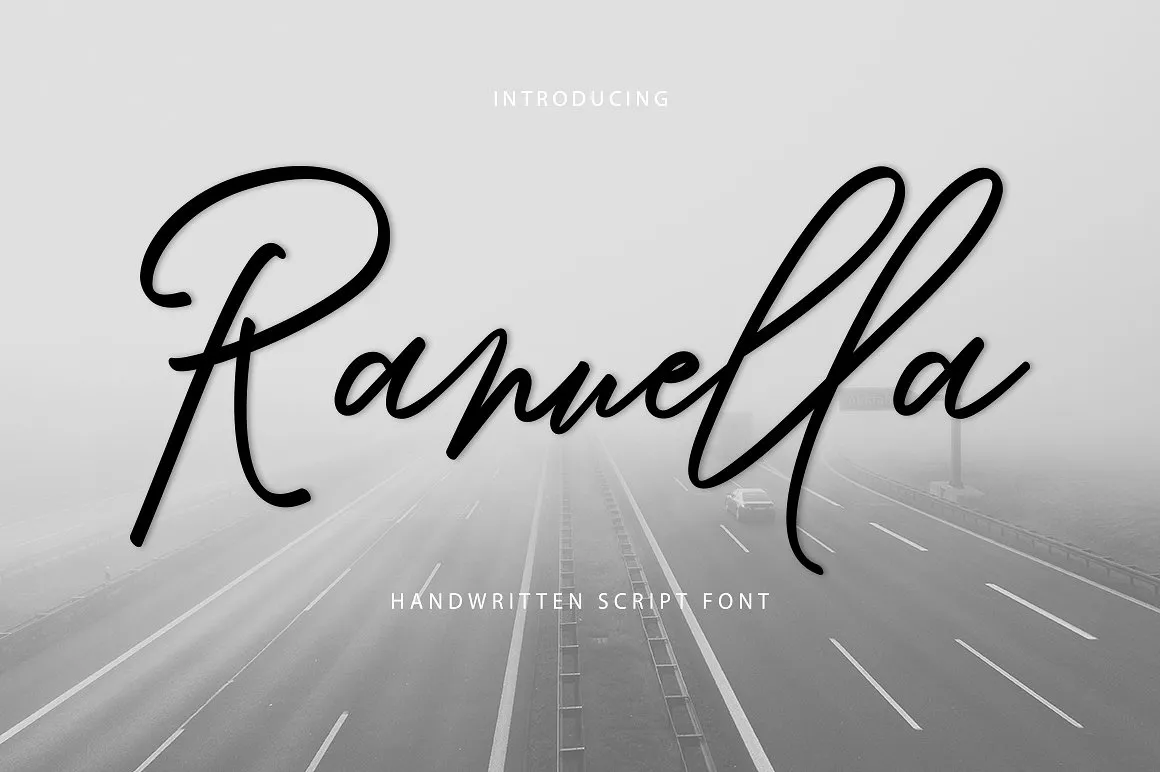
Ranuella Script Font – Download Grátis
Aqui está uma descrição para a página de download da fonte ‘Ranuella Script Font’ que cumpre com as regras fornecidas: Compreende o valor do design original e fluido? A Ranuella Script oferece exatamente isso. Takiyuddin, nosso designer visionário, criou uma fonte de script aparentemente escrita a mão, perfeita para aqueles que buscam um toque autêntico em seus projetos. Com mais de 350 gílias disponíveis, Ranuella não decepciona e pode ser usada em uma variedade de contextos – desde pequenos detalhes até grandes títulos. Além disso, a fonte é um presente para designers avançados que buscam explorar todas as possibilidades das características do OpenType. Alternativas alternadas, conjuntos estilísticos e alternações contextualizadas estão presentes em um número impressionante de caracteres e combinam para criar uma experiência visual única. Através dos programas como o Adobe Illustrator, InDesign ou Photoshop, os designers podem explorar a profundidade da Ranuella Script Font. Inspirado por artistas reais que utilizaram sua habilidade em diferentes campos, a Ranuella é uma fonte de script ideal para aqueles buscando criar um design que seja autêntico e impecável. Que tal experimentar o poder criativo que esta fonte tem para transformar seu trabalho?